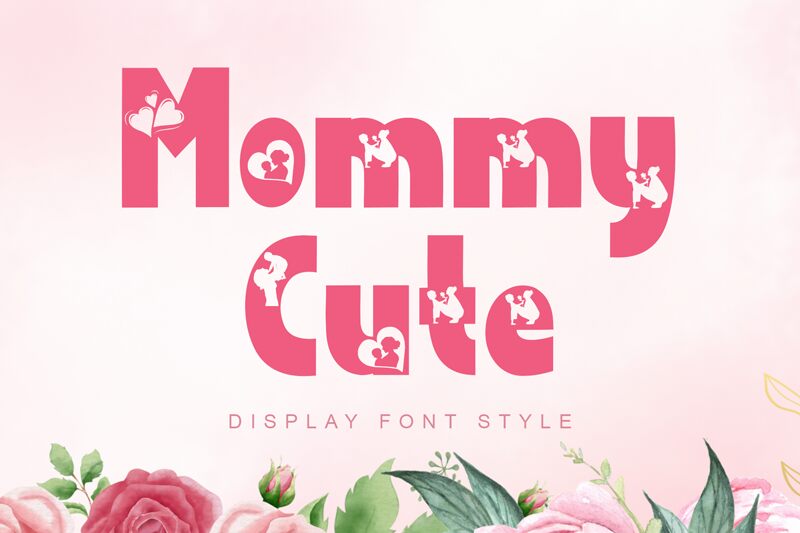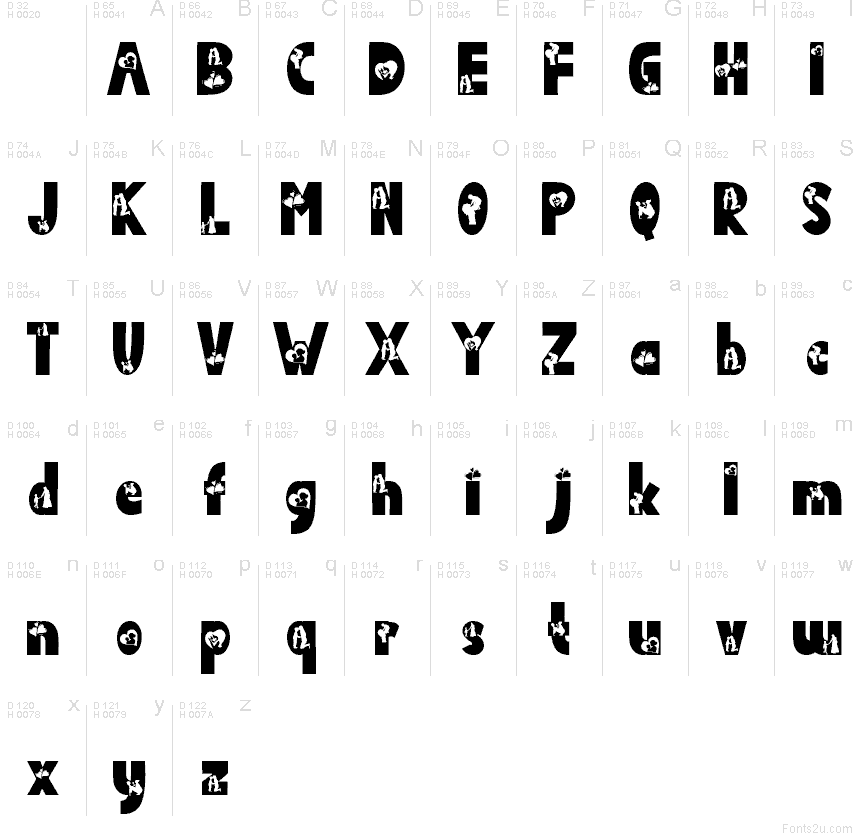
Mommy Cute
Mommy Cute de Yoga Letter est une police d'affichage décorative gratuite aux formes arrondies et massives, agrémentée de petits motifs de cœurs et de couples intégrés à certains caractères. Les lettres sont compactes et solides, avec des courbes fluides et quelques détails de découpe ludiques qui confèrent au design un côté romantique et artisanal.
Mommy Cute est idéale pour les invitations de mariage, les cartes de Saint-Valentin, les bannières de fête, les étiquettes cadeaux, le branding de boutiques et les visuels pour réseaux sociaux, car les cœurs intégrés portent le thème sans nécessiter d'ornements supplémentaires. Cette police gratuite convient également parfaitement aux citations courtes, logos et titres décoratifs lorsque vous souhaitez ajouter une touche chaleureuse et personnelle au lieu d'une police classique.